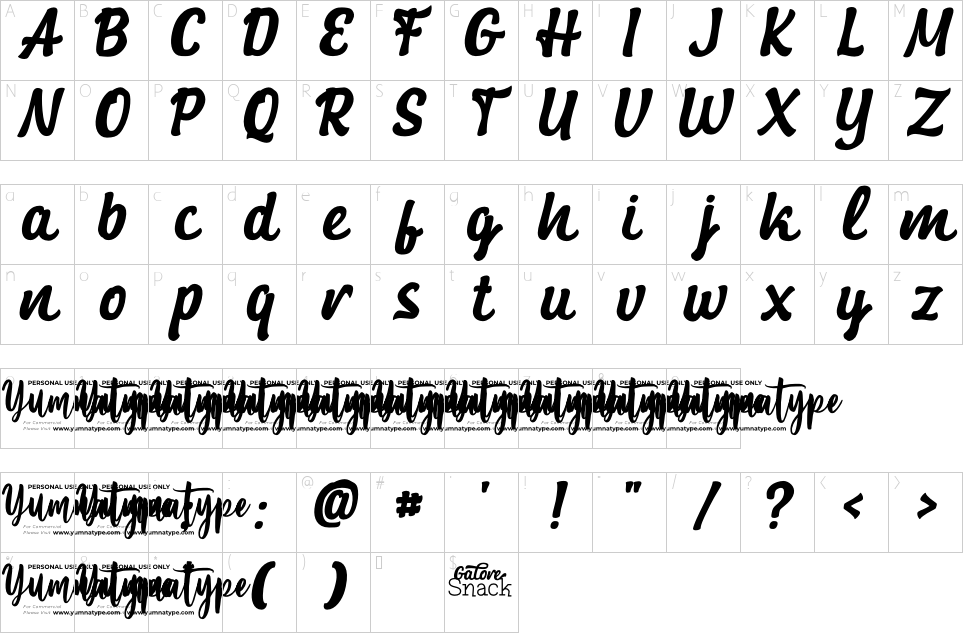
Galore Snack Font – Download Grátis
A Galore Snack é uma fonte que traz alegria e leveza para qualquer projeto editorial ou design gráfico, especialmente quando se trata de textos fáceis e confortáveis para ler. Desenvolvida pela Yumna Type, essa fonte rápida e divertida foi projetada para criar um ambiente acolhedor, perfeito para publicações que buscam uma aparência descontraída sem abrir mão da qualidade. Ideal tanto para aplicativos Windows quanto para Mac, a Galore Snack é uma opção gratuita perfeita para designers que prezam pelo bom gosto e por adquirir fontes de qualidade. Com 4.377 downloads realizados desde sua disponibilização, percebe-se o crescente reconhecimento desta fonte entre os criativos digitais. Seja para títulos ressaltados ou textos em um post da página do Facebook, a Galore Snack traz uma pitada de diversão e personalidade a qualquer projeto que leve à mesa.